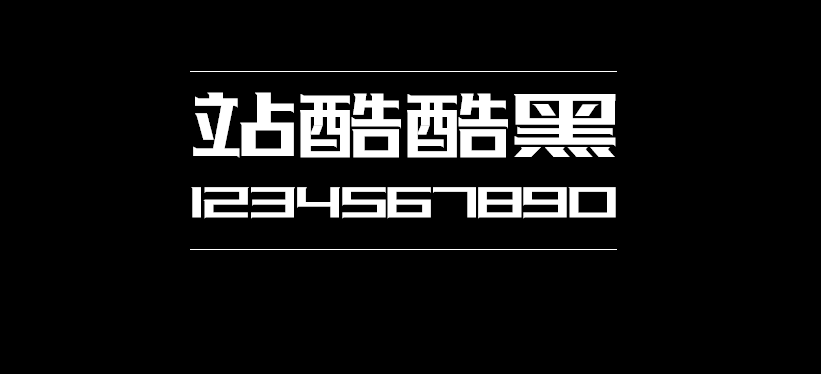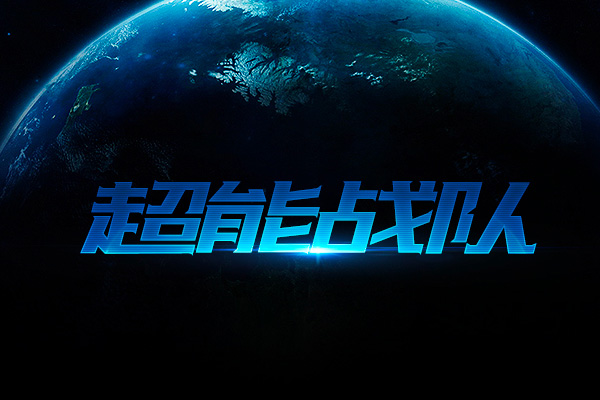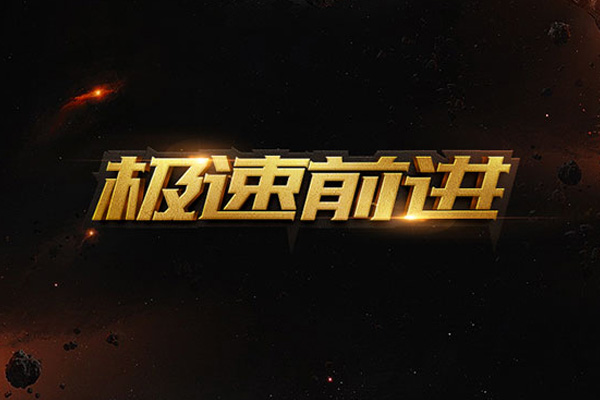
站酷酷黑体
由胡晓波发起,字游工作室成员进行基础字形设计。胡晓波设计班十名学员共同设计完成。 [站酷酷黑体]在站酷十周年之际横空出世。字形笔画粗犷有力,用宽扁型的字面构建出厚重的字体形态,笔画细节上的修饰既增强了字体的设计感,又让字体多了一些小小的精致感,中宫的饱满使得文字之间的排版组合非常醒目好看,于2016年7月发布。包含3500个常用字,52个英文字母,10个阿拉伯数字。
站酷酷黑体效果预览